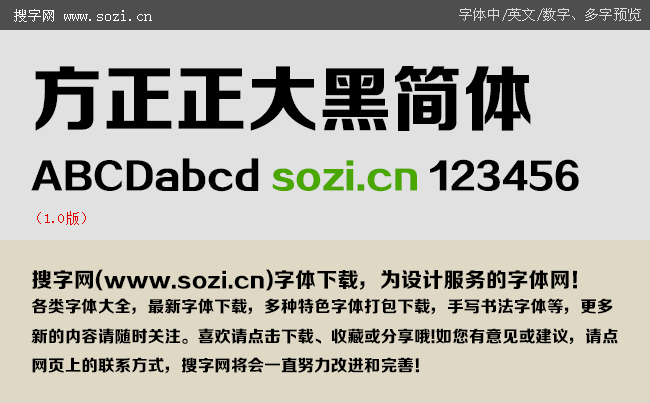
方正正大黑簡體
搜字網(wǎng)提供一方正正大黑簡體中文藝術(shù)字體下載,正黑體取傳統(tǒng)黑體結(jié)構(gòu),筆形全部采用平行、垂直與弧度的流線形設計,簡潔易識、美觀大方,具有個性,加之鏡像對稱的現(xiàn)代構(gòu)成形式,達到莊重與簡潔有機融合、設計感與閱讀功能兼?zhèn)涞淖罱K效果。適合書籍排版,報紙排版,海報設計,包裝設計等廣告設計場合應用。